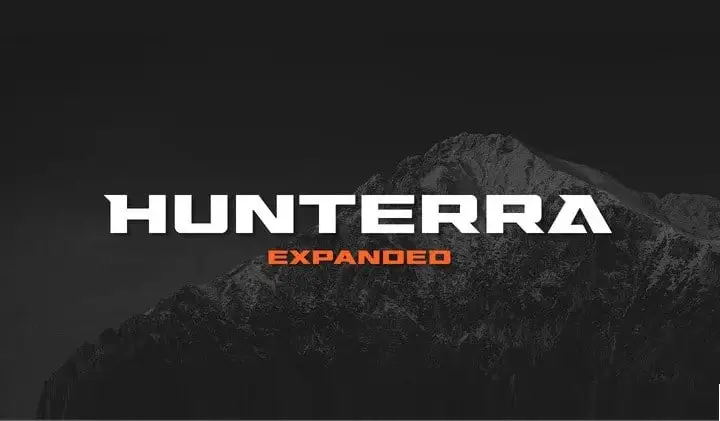
Hunterra Display Font é uma nova escolha para designers que buscam um estilo visual atraente e original. Essa fonte variável tem um design único e destaca-se das demais, criada pelo talentoso font designer Variatype. Com seu forte carácter e linhas definidas, Hunterra Display Font foi projetado especificamente para projetos de identidade, sendo perfeitamente adequado para a criação de marcas e logotipos. Em um mundo onde as marcas buscam se destacar, o design desta fonte é uma ótima opção para quem deseja criar um impacto imediato e único em sua marca ou projeto visual.